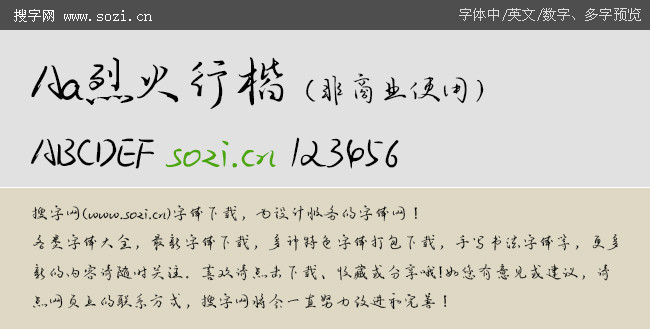
Aa烈火行楷
搜字網(wǎng)給大家提供一款A(yù)a烈火行楷(非商業(yè)使用)中文字體下載,該字體是一款手寫風格的字體,字體筆觸較為纖細靈動,字形灑脫,流暢自然,具有很好的視覺感。適合書裝設(shè)計、包裝設(shè)計、海報設(shè)計等應(yīng)用(此字體為個人非商用版,商用可以聯(lián)系QQ:1006760504)。